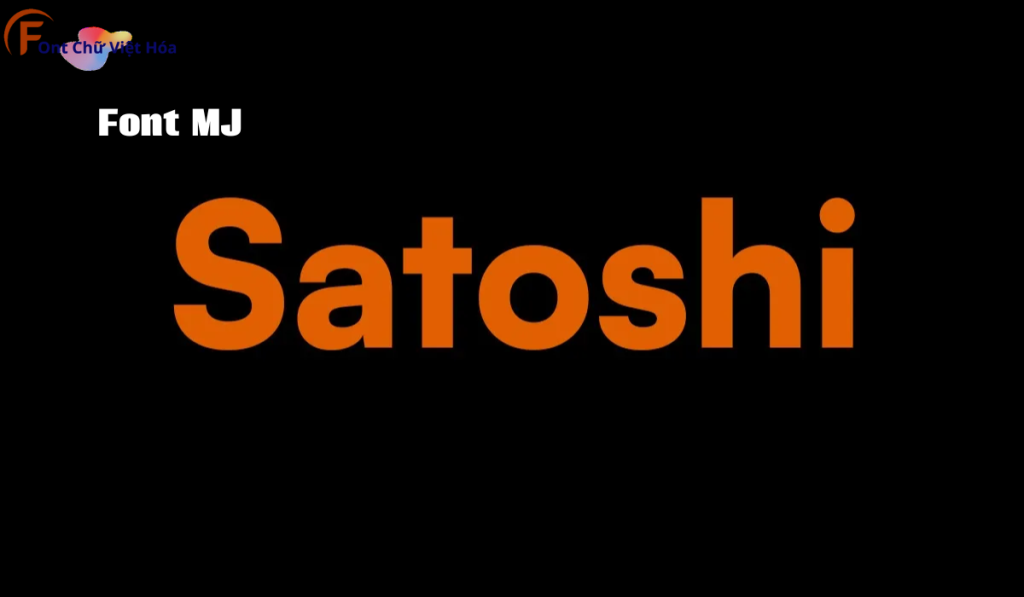
Font MJ Satosshi Việt Hóa
Tác giả: MJ
Bộ Font: MJ
Font MJ Satosshi Việt Hóa là một font chữ không chân hiện đại, thuộc bộ font MJ. Được thiết kế với mục tiêu mang lại sự tinh tế và thanh lịch, font này phù hợp cho các dự án thiết kế như website, tài liệu, và bao bì sản phẩm. Với các nét chữ rõ ràng và độ dày đều đặn, Font MJ Satosshi Việt Hóa không chỉ dễ đọc mà còn tạo cảm giác chuyên nghiệp. Việc Việt hóa font giúp người dùng dễ dàng sử dụng trong các thiết kế tiếng Việt, mang lại sự tiện lợi và thẩm mỹ cao.